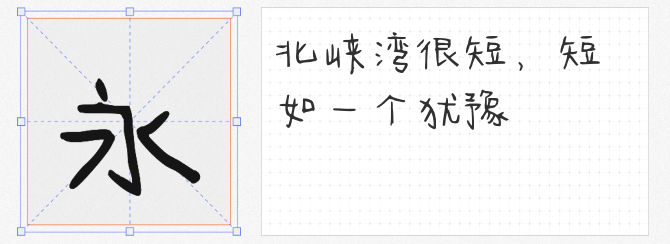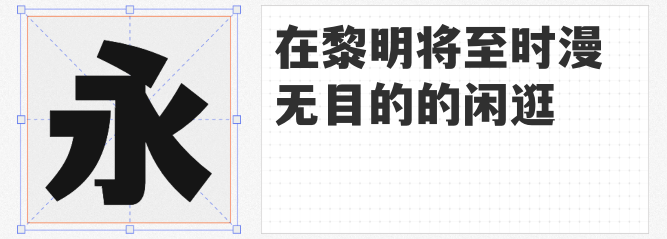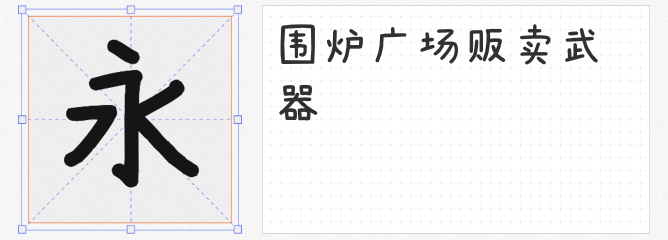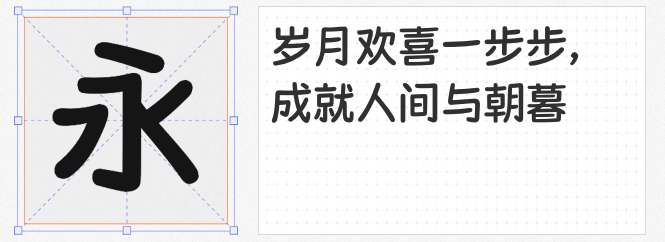
母婴类商品设计需兼顾视觉吸引力与情感温度,字体选择尤为重要。以下四款免费商用字体,以温暖笔触和童趣造型,为母婴产品设计注入治愈能量:
1.今年也要加油鸭
这款字体的短促笔画与稚拙骨架,恰似孩童学步时的摇摆姿态。圆润的转角设计弱化了黑体的生硬感,在奶瓶包装、童装标签或启蒙绘本中运用,能瞬间唤醒观者的保护欲。其笨拙可爱的特质,既适配萌宠零食包装的活泼调性,也能为母婴用品传递"被温柔以待"的品牌温度。
2. 荆南麦圆体
受韩国综艺谚文字体启发的荆南麦圆体,将手写温度注入现代设计。均匀饱满的笔画如棉花糖般柔软,在婴幼儿辅食包装或玩具说明书中使用,既能清晰传递信息,又自带安抚属性。其清新的断笔处理避免过度甜腻,使可爱风格保持适度呼吸感,尤其适合需要兼顾功能性与情感表达的设计场景。
3. 文道潮黑体
当设计需要平衡潮流感与典雅气质时,这款黑体成为独特选择。其刚柔相济的笔锋既保留黑体的现代简约,又融入宋体的雅致曲线,在高端母婴用品手册或品牌LOGO中运用,既能彰显专业度,又避免过度严肃。方正字形传递出可靠的信任感,恰如父母对孩子的守护。
4. 素材集市康康体
这款手写字体以天然的不完美展现生命力,如同孩子稚嫩的笔触。略带歪斜的字形充满成长故事感,特别适合用于手工母婴产品包装或成长纪念册设计。其温暖怀旧的气质,能让消费者在阅读产品说明时,同步感受到品牌背后的人文关怀。
四款字体各具性格:憨态可掬、甜蜜治愈、优雅克制,共同构建了母婴设计的情感坐标系。建议根据具体场景灵活搭配——用圆润字体传递安全感,以典雅字形塑造专业形象,借手写风格拉近距离,让文字成为产品设计中最温暖的叙事者。